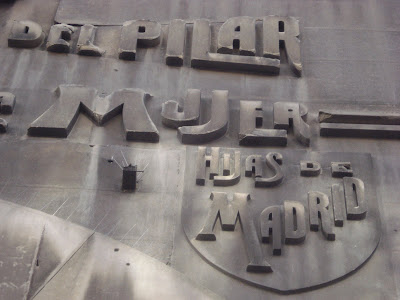
Curtidos Lobejón
En la avenida de Menéndez Pelayo 15, el cartel sobre la tienda lo forman números y letras de bronce en relieve, resaltando sobre un fondo negro.
Instituto del Pilar (Colegio Nª Sra de las Delicias)
En el Paseo de las Delicias 67.
Construido a comienzos del siglo XX en un tardío estilo neomudéjar, la tipografía en su fachada presenta evidentes rasgos modernistas.
Se ignora quién la diseñó, como tampoco se sabe quién fue el arquitecto del edificio o si ambas obras se deben a la misma persona.
Radio Electra
En Hortaleza 9, la tienda todavía permanece abierta.
Edouard
Es una tienda de artículos de peluquería en Gran Vía 58.
Su fachada (construida probablemente en los años 40 o 50 del siglo XX) parece destinada en principio a otro tipo de negocio más selecto, quizá el que ocupara anteriormente el local, una joyería o una sastrería para caballeros solventes.
De otro modo no se explica la elegancia y el lujo que transmite con sus materiales nobles y su estilo neoclásico.
El logo elegido, caligrafía americana en metal dorado con rúbrica, como una firma estilizada, serviría en ese caso perfectamente para realzar la categoría del local.
Marín muebles
En Arenal 21, esquina con la calle de las Fuentes.
Tienda especializada en muebles y objetos variados para decoración, incluyendo réplicas de juguetes antiguos.